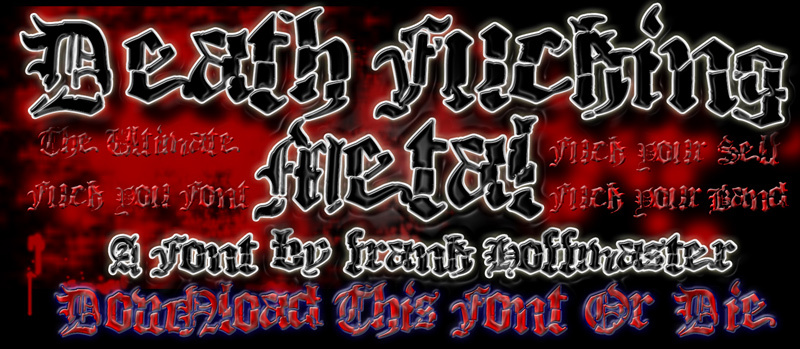
Death Fucking Metal ist eine kostenlose, verzerrte Blackletter-Display-Schrift mit einer rauen, wilden Attitüde. Die Buchstaben kombinieren mittelalterliche Blackletter-Wucht mit abgehackten Ecken, unebenen Verbindungen und scharfen Spitzen – das ganze Design wirkt eher wie ein zerfetztes Band-Logo als wie eine brave Neuinterpretation.
Die Schrift eignet sich perfekt für Poster, Alben-Cover, Zines, Festival-Flyer und Merchandise, wenn der Titel diese feindselige, düstere Underground-Stimmung braucht. Als kostenloser Font eignet sie sich auch hervorragend für Überschriften, kurze Header und grobe Monogramme, da die gebrochenen, altenglischen Formen die Message transportieren, noch bevor man sie liest.